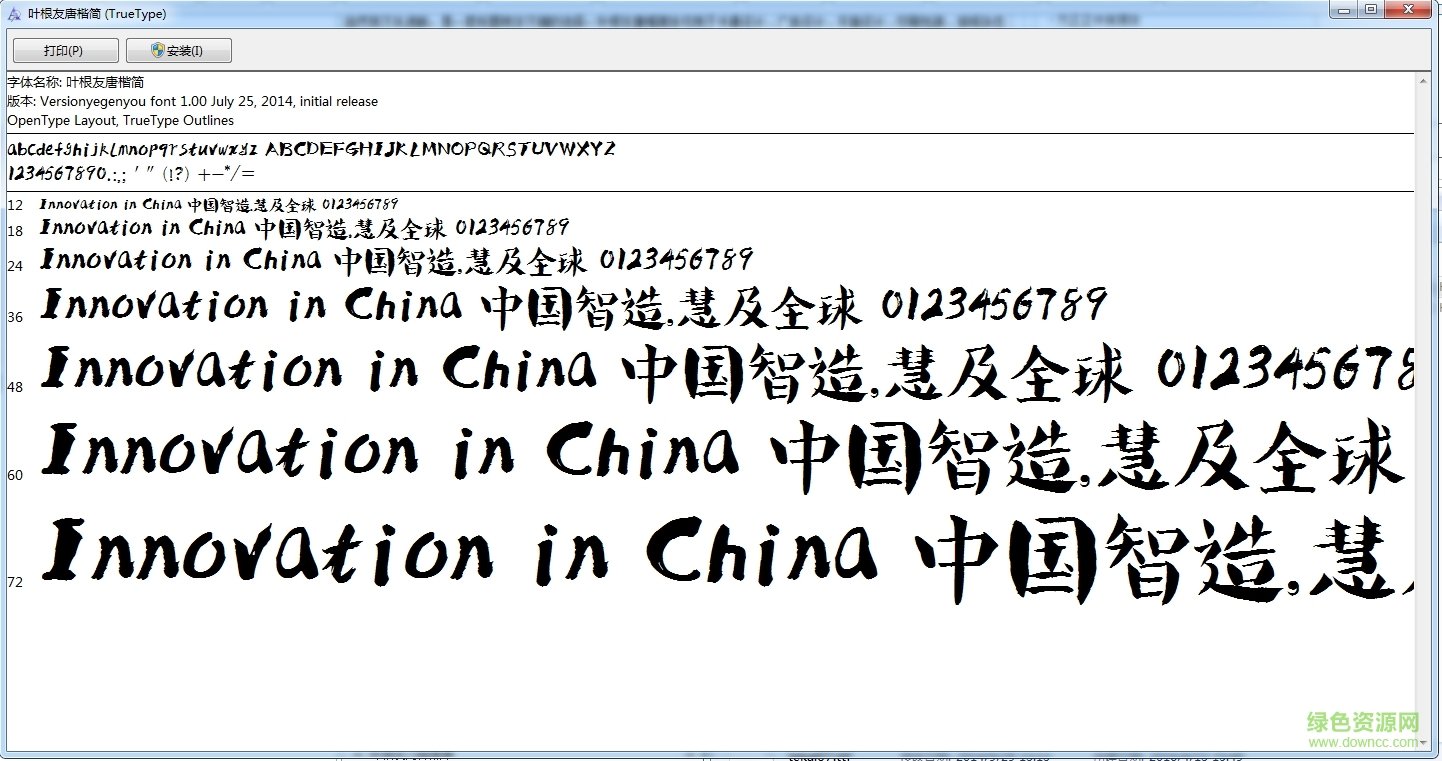
葉根友唐楷簡(jiǎn)是特楷字體的姊妹風(fēng)格字體,在延續(xù)特楷字型基礎(chǔ)上重新創(chuàng)意,整個(gè)字型較之前的特楷更加嚴(yán)謹(jǐn),風(fēng)格遒勁,自然而不失灑脫,是一款標(biāo)題用字不錯(cuò)的選擇。葉根友唐楷簡(jiǎn)體可用于卡通設(shè)計(jì)、廣告設(shè)計(jì)、平面設(shè)計(jì)、印刷包裝、報(bào)紙雜志等行業(yè),喜歡的小伙伴快來(lái)綠色資源網(wǎng)下載吧!